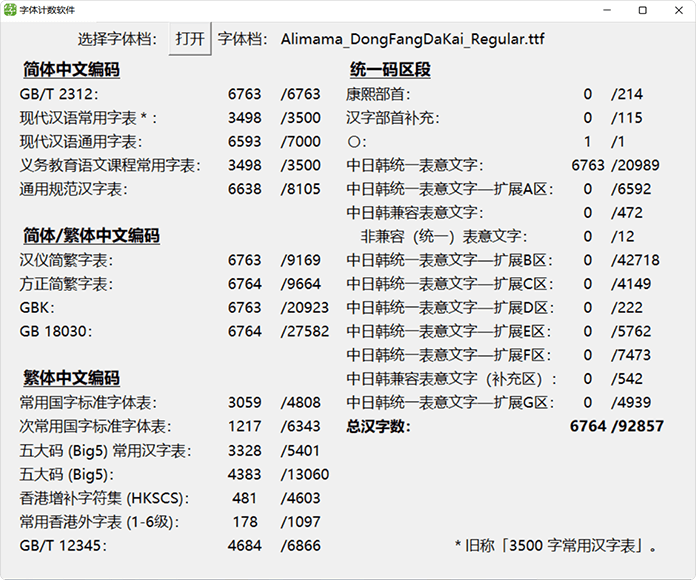
阿里妈妈东方大楷:基于颜真卿多宝塔碑算法生成的免费商用字库
字体作者:阿里妈妈 (中国大陆) 字体字重:1个
阿里妈妈东方大楷是基于颜真卿的多宝塔碑算法生成并结合人力完成的一套字库,机器学习到了颜体的丰腴厚重之感,在笔画的描摹上做到了传统书法的收放起伏,规范了骨架、笔画,还原了书法中的落笔、转笔、藏锋、护尾等书写韵味,使整体更饱满、圆融、浑厚。
阿里妈妈东方大楷为中文简体字库,收纳的中文字符包括但不限于GB2312,共计6763个汉字;英文大小写(含全角、半角、合体字等)共105个;常用标点符号共175个,总计7043个字符。
检查了一下,这个字体的“靡”字字形在描边处理后出现了问题,用FC检查了一下,笔画之间线条没有处理好,希望可以修一下
阿里妈妈东方大楷:真的很不错。可以理解为 原版颜体。更重要的是,这款字体的发布协议,没有像以前阿里系的字体(只能从官方下载,明确不允许第三方网站提供字体包)。现在的协议宽松了一些,相当于允许字体网站转发字体包了。想必是阿里送给大家的新年大礼包!字体用来写对联,楼台场馆题字,都是极好的。
• 字数能多点就好了,至少也要包括通用规范8105个字符